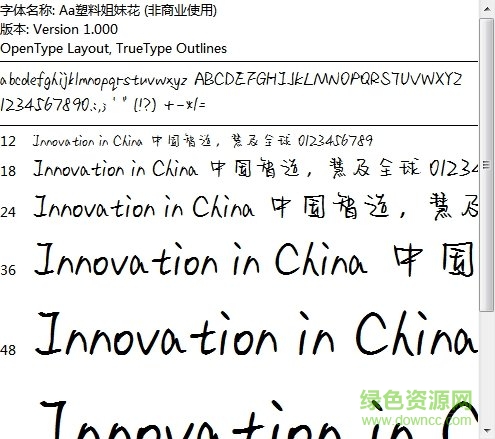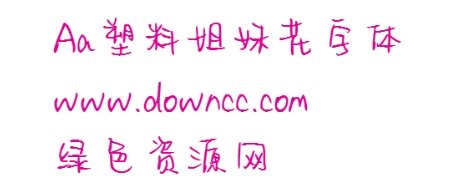
aa塑料姐妹花字體
塑料姐妹花字體是一款非常也使用的女生字體,字體拜托了中規(guī)中矩的造型,更加的連貫而不潦草,有著極佳的個性呈現(xiàn)方式,是一款比較強(qiáng)勢的手寫字體。
塑料姐妹花什么意思
塑料姐妹花,該詞源自于之前微博上的一個段子“好姐妹的感情就像塑料花,特別假,但是卻永不凋謝”,都說三個女人一臺戲,五個女人能建六個群,因此作為網(wǎng)絡(luò)語產(chǎn)生的“塑料姐妹花”一詞常常用來形容一些女生之間勾心斗角,虛與委蛇的面子社交,特別虛假不走心。
海報設(shè)計、廣告創(chuàng)意、商業(yè)策劃等領(lǐng)域中,有一款干凈簡潔的字體,能讓你的文字內(nèi)容大方光彩,凸顯其藝術(shù)效果,而塑料姐妹花體字體可以很好的滿足你的要求,不信,就來本站免費(fèi)試試吧!